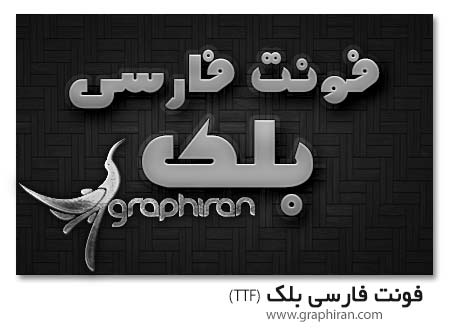
دانلود فونت فارسی مثلث A Mosalas Farsi Font
فونت فارسی مثلث یکی از زیباترین فونت های فارسی گرافیکی مناسب برای طراحی لوگو و تایپوگرافی می باشد. این فونت فارسی با طراحی خاص خود که دارای حروف شکسته می باشد می تواند گزینه مناسبی برای طراحی عنوان پوستر و بنر نیز باشد. طراحان سایت و طراحان گرافیک می توانند با استفاده از این فونت جدید فارسی زیباترین نوشته ها را خلق کنند. امیدواریم این فونت مورد توجه شما قرار گیرد. در ادامه مطلب می توانید فونت فارسی مثلث را دانلود کنید.
فونت فارسی مثلث
دانلود فونت فارسی سارای A Saray Farsi Font
فونت فارسی سارای یکی از جدیدترین فونت های رایگان فارسی می باشد. این فونت که تغریبا از فونت های ناخوانا می باشد برای طراحی لوگوتایپ، لوگو و انواع تایپوگرافی می تواند مورد استفاده قرار گیرد. فاصله های زیاد بین حروف و دندانه ها به شما در طراحی تکسچرهای بین این مناطق در تایپوگرافی یا طراحی لوگو کمک می کند. همچنین ناخوانا بودن آن را می توان از ویژگی های مهم در طراحی آثاری دانست که قرار است بیننده با دقت بیشتری به آنها توجه کند.
فونت فارسی سارای
دانلود فونت فارسی مکتوب A Maktoob Farsi Font
فونت فارسی مکتوب یکی از جدیدترین و زیباترین فونت های فارسی است که می توانید آن را هم اکنون از گرافیران دانلود کنید. طراحی چشم نواز این فونت فارسی رایگان می تواند باعث جلب توجه بینندگاه شود. طراحی جالب این فونت که نوعی طراحی فانتزی است آن را برای انواع طراحی ها مناسب می سازد. شما در ادامه مطلب می توانید این فونت زیبا را از گرافیران دانلود و در طرح های گرافیکی خود استفاده کنید.
فونت فارسی مکتوب
دانلود فونت انگلیسی ضخیم و مدرن MB SixtyThree
یک فونت جدید انگلیسی بسیار زیبا با طراحی مدرن و ضخیم به نام SixtyThree را هم اکنون برای شما علاقه مندان به گرافیک و طراحی آماده دانلود کرده ایم. این فونت انگلیسی زیبا و بی نظیر برای طراحی مجلات، لوگوتایپ، پوستر، آلبوم ها و دیگر انواع طرح های گرافیکی قابل استفاده می باشند. شما در ادامه مطلب می توانید این فونت جذاب انگلیسی را دانلود کنید.
فونت جدید انگلیسی
دانلود فونت فارسی زیبا و جدید بلک Far Black Farsi Font
فونت فارسی جدید بلک یکی از زیباترین فونت های فارسی با طراحی ضخیم می باشد که مطمئنا بسیاری از شما طراحان گرافیک به آن علاقه مند خواهید شد. این فونت فارسی زیبا برای طراحی انواع پوستر، بنر، تراکت حتی برای طراحی لوگو نیز می تواند مورد استفاده قرار گیرد. شما در ادمه مطلب می توانید این فونت فارسی گرافیکی را به صورت رایگان دانلود کنید.
فونت فارسی جدید بلک
دانلود فونت فارسی پیکسل A Pixel Farsi Font
در این پست ۲ فونت فارسی پیکسلی بسیار زیبا مناسب برای طراحی های گرافیکی فانتزی را برای شما آماده دانلود کرده ایم. فونت های پیکسلی فارسی با طراحی جذاب و ساده خود می توانند زینت بخش طرح های گرافیکی شما مانند کارت ویزیت، بنر یا پوستر و بیلبورد باشند. این فونت های فارسی زیبا در نرم افزارهای فتوشاپ و ورد قابل استفاده می باشند. در ادامه مطلب می توانید فونت های فاریی پسکل ۱ و پیکسل ۲ را از گرافیران دانلود کنید.
فونت فارسی پیکسلی
دانلود فونت انگلیسی گرافیکی و حرفه ای Lampa
فونت انگلیسی Lampa یکی از جدیدترین و زیباترین فونت های انگلیسی است که به صورت حرفه ای طراحی شده است و مناسب برای انواع طرح های گرافیکی می باشد. شما با استفاده از این فونت انگلیسی زیبا و ابتکاری می توانید زیباترین طرح های گرافیکی خلق کنید. طراحی جذاب این فونت در نوع خود بی نظیر بوده و مطمئنا مورد توجه بسیاری از طراحان گرافیک قرار خواهد گرفت. شما در ادامه مطلب می توانید این فونت انگلیسی حرفه ای را به صورت رایگان دانلود کنید.
فونت انگلیسی Lampa